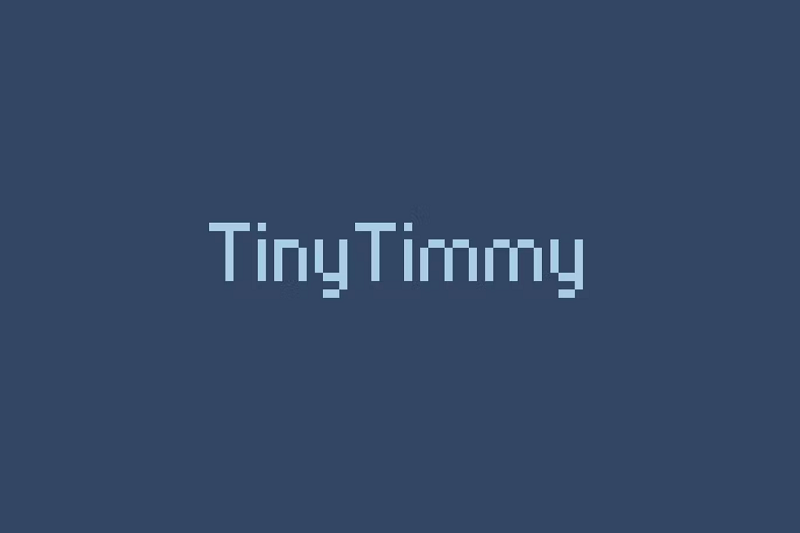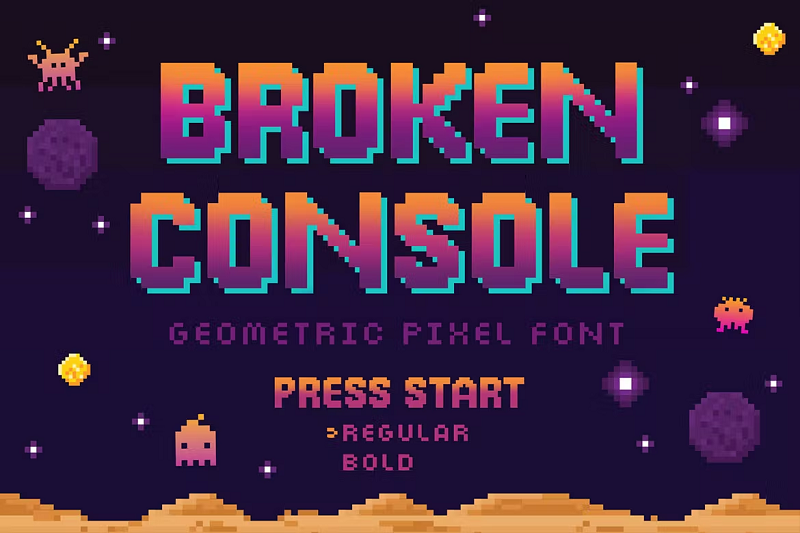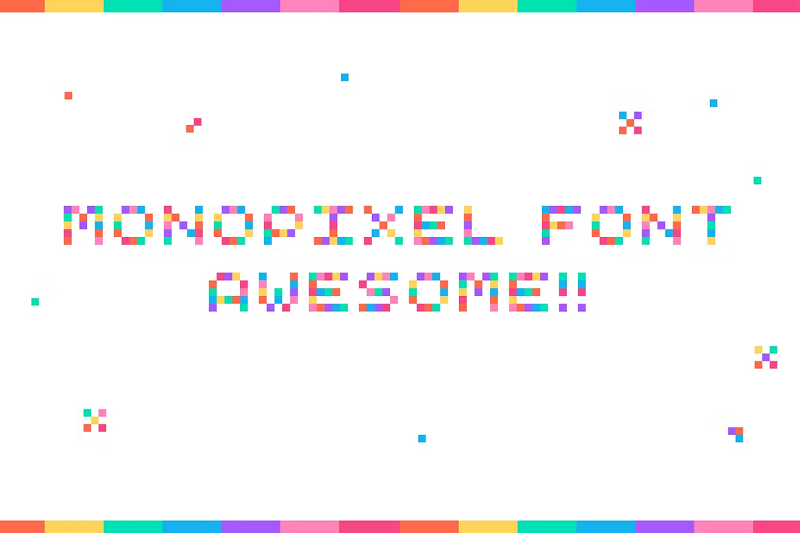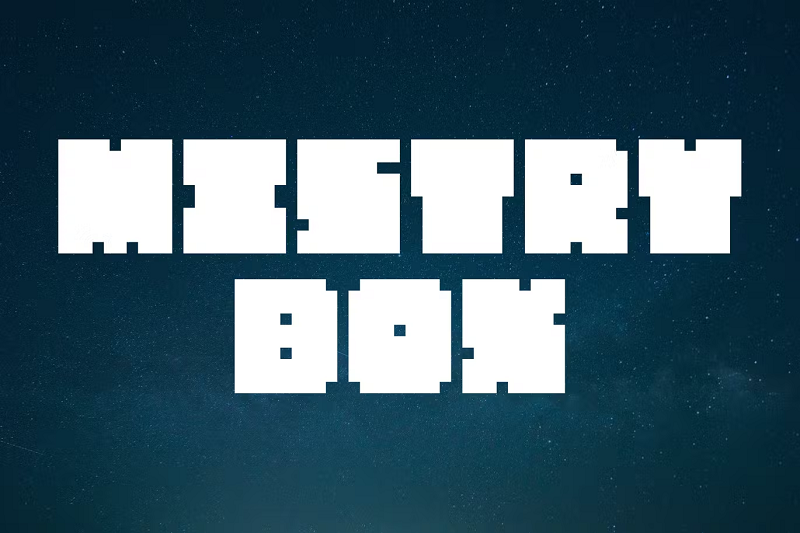
Die 22 besten Pixel-Fonts, um Ihre Designs zu verbessern (2022)
Veröffentlicht: 2022-07-14Möchten Sie Ihre Designs mit einer coolen Pixelschrift aufwerten? Egal, ob Sie ein Poster zum Thema Gaming erstellen oder Ihren Designs ein Retro-Feeling der 80er Jahre verleihen möchten, Pixelschriften können eine gute Wahl sein.
Es kann jedoch schwierig sein, die perfekte Pixelschriftart zu finden. In diesem Artikel werfen wir einen Blick auf 22 der besten Pixel-Fonts, die für jede Art von Design verfügbar sind.
Bereit? Lass uns anfangen
1. Game Over – Unsere Top-Auswahl
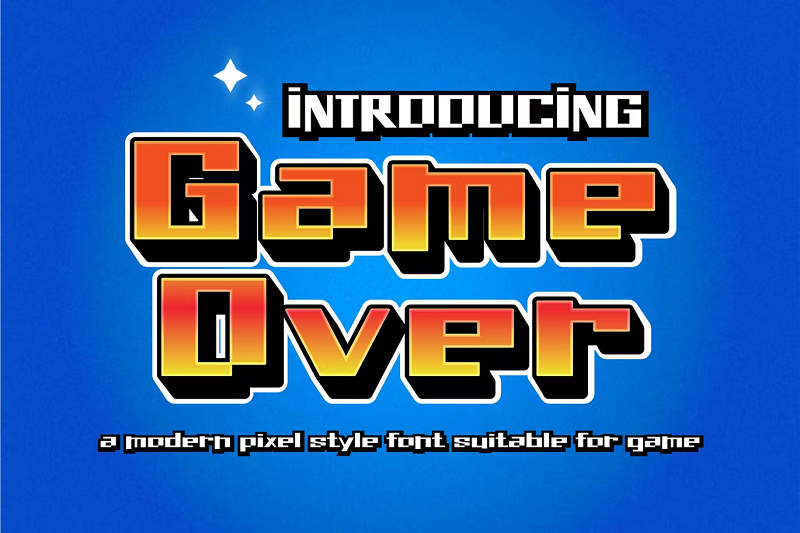
Game Over ist eine moderne Schriftart im Pixelstil, die sich am besten für Spielgrafiken und -titel eignet, aber auch in vielen anderen Designs gut funktionieren könnte. Es ist in den Dateiformaten OTF, TTF und WOFF erhältlich und enthält alle üblichen Glyphen sowie Sonderzeichen und Alternativen, auf die nur Programme zugreifen können, die OpenType-Funktionen unterstützen (z. B. Photoshop, Illustrator usw.).
Warum es unsere erste Wahl ist
Dies ist eine der beliebtesten Schriftarten im Pixelstil auf Envato Elements, und es ist klar, warum. Es ist eine klassische Pixelschrift mit Buchstabenformen, die auch aussehen, als wären sie aus Blöcken gebaut.
Es ist eine Hommage an die Art von Vintage-Bitmap-Schriftarten mit niedriger Auflösung, die Sie in klassischen Arcade-Spielen sehen würden, aber im Gegensatz zu diesen Old-School-Schriftarten hat Game Over eine moderne Wendung, die es besser für modernere Designs geeignet macht.
2. Pixelbit
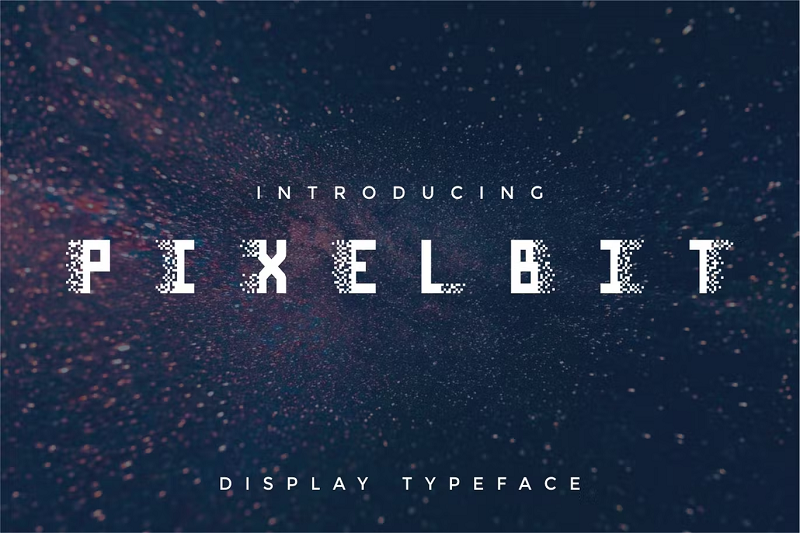
Pixel Bit ist eine einzigartige, futuristische Displayschrift mit interessantem Design. Die Buchstaben sind blockig mit geraden Kanten und eckigen Ecken, aber es sind die Alternativen, die dieser Schrift ihren Charakter verleihen.
Sie können die Alternativen verwenden, um coole „digitale Punktpixel“ auf jeder Seite jedes Buchstabens hinzuzufügen: oben, unten, rechts oder links. Sobald Sie die digitalen Punktpixel hinzufügen, sieht es so aus, als würden die Buchstaben in den Cyberspace zerfallen und in ihre Pixelbestandteile zerfallen. Außerdem ist es ein wirklich cooler Effekt, der gut auf Sci-Fi-Filmplakaten und futuristischen Spielen funktionieren würde.
3. Mainport Pixelate
Mainport ist eine Display-Schriftart, die sich von den pixeligen RPGs alter Zeiten inspirieren lässt. Es ist extrem nostalgisch und erinnert an 2D-RPG-Spiele der alten Schule. Die Buchstabenformen sehen aus, als wären sie mit der absoluten Mindestanzahl von Pixeln hergestellt worden. Der Download enthält OTF- und TTF-Dateien, Glyphen sowie Groß- und Kleinbuchstaben, Zahlen und Satzzeichen.
4. Pixelhandwerk
Pixel Craft ist eine niedliche, schrullige Pixelschrift mit verspielten Buchstabenformen und absichtlich chaotischen Strichen. Es ist entspannt und eignet sich perfekt für Kinderspieldesigns, Poster und auch digitale Produktdesigns.
5. Pixel 1 Farbschrift
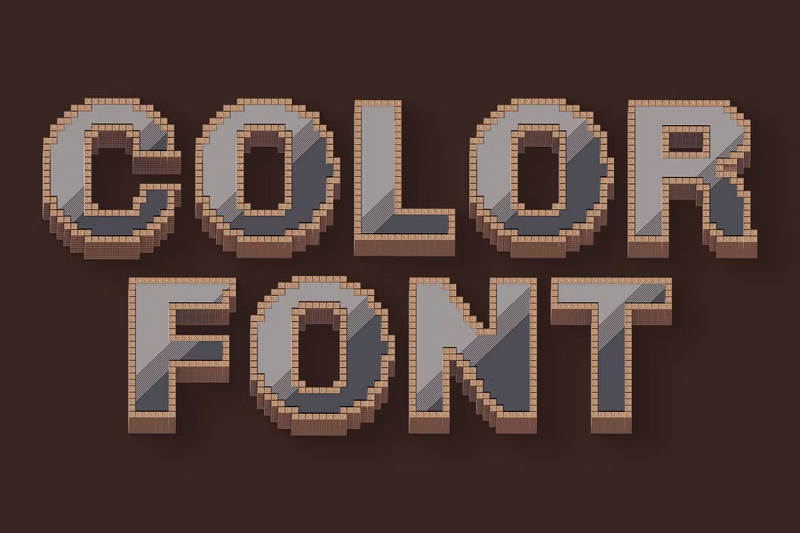
Pixel 1 ist eine Color-SVG-Schriftart. Es sieht aus, als hätte der Designer es aus 3D-Pixelblöcken gebaut. Für Uneingeweihte: Farb- oder SVG-OpenType-Schriftarten sind eine neue Art von Schrifttechnologie, mit der Designer zusätzliche Details wie Farben, Farbverläufe und Texturen in die Datei integrieren können. Dadurch sind sie in der Lage, aufwändige, hochdetaillierte Schriftarten mit coolen 3D-Effekten wie dieser zu erstellen.
6. Pixel sind schlecht geworden
Pixels Gone Bad ist eine chaotische dekorative Schriftart, die sich perfekt für Poster, Titel und andere große Displays eignet. Der Designer hat es so aussehen lassen, als wären die Glyphen aus Dutzenden einzelner Pixelblöcke aufgebaut, die drunter und drüber gehen. Es ist eine Schrift, die ungeordnet, geordnet und auch voller Energie ist.
7. Bit Game Retro-Pixel-Schriftart
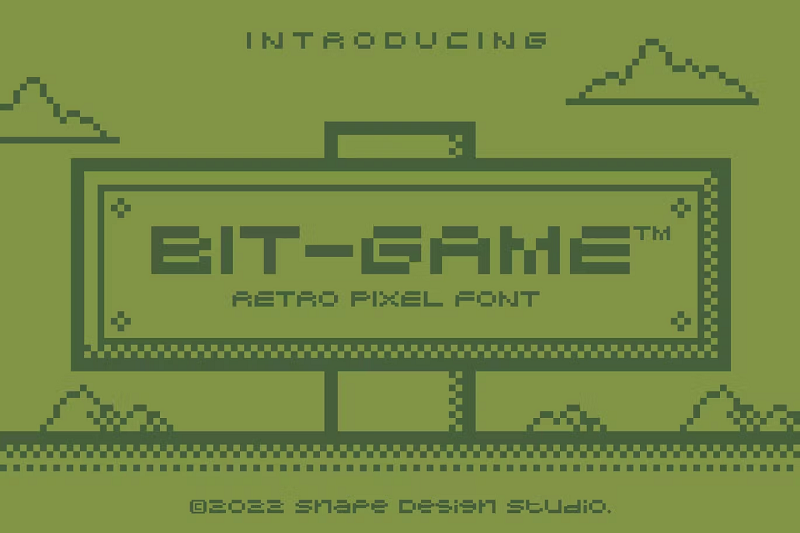
Bit Game ist eine weitere Retro-Schrift, die Pixel-Fonts der alten Schule emuliert. Die schrulligen, pixeligen Charaktere passen perfekt zu all Ihren Gaming-bezogenen Designs. Sie könnten auch gut auf Buchumschlägen, Markenlogos, Postern usw. funktionieren.
Verwenden Sie Pixel-Schriftarten für Poster und Kopfzeilen
Pixel-Fonts sind wirkungsvoll, retro und auch sehr cool. Auf Plakaten und Kopftexten funktionieren sie jedoch viel besser als in größeren Textblöcken. Wenn Sie daran denken, eine Pixelschriftart in Ihren Designs zu verwenden, ziehen Sie in Betracht, sie als Ihre Kopfzeilentexte zu verwenden und sie mit einer besser lesbaren und einfachen Schriftart für größere Textblöcke zu kombinieren.